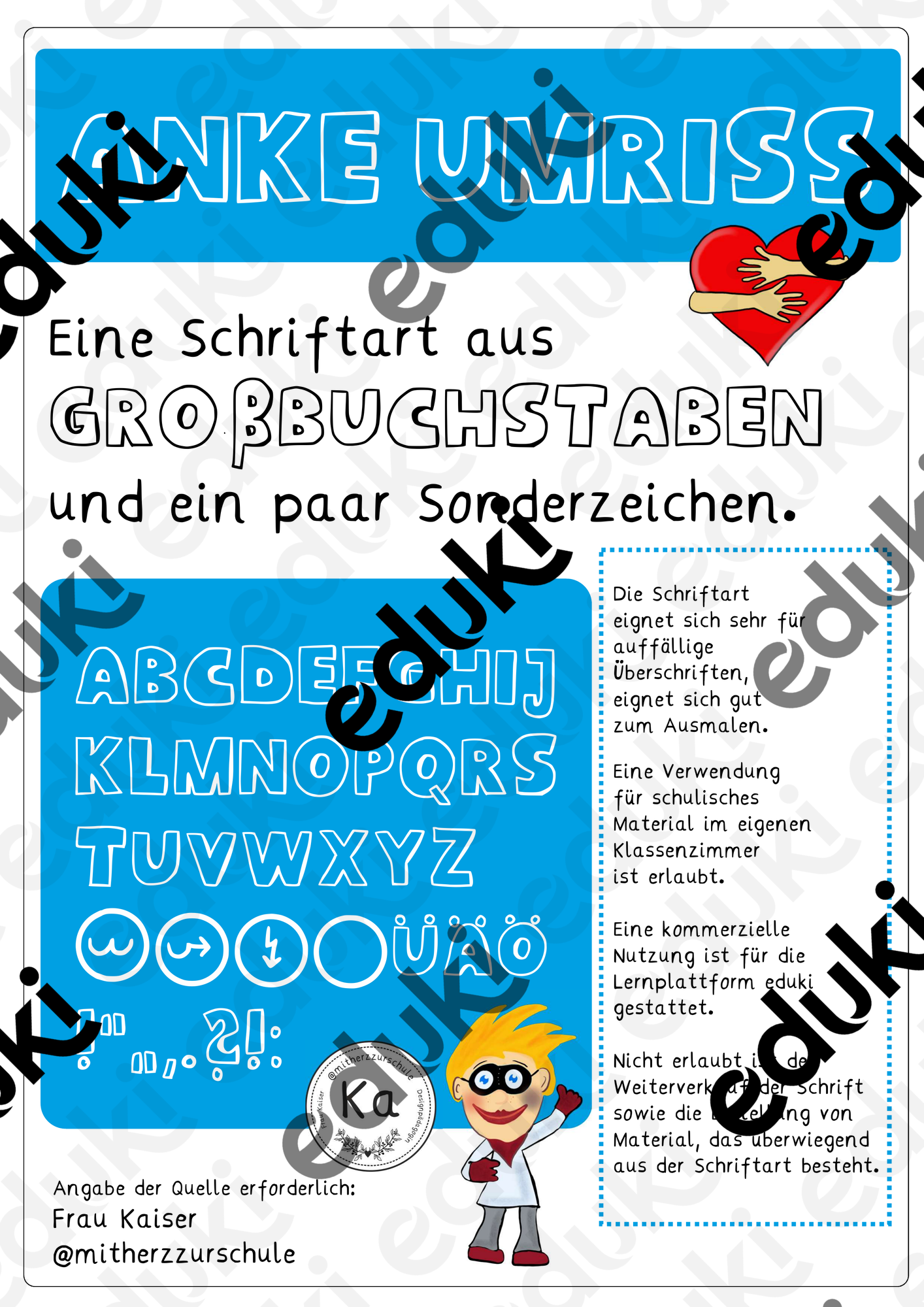
selbst erstellte Schriftarten - Schriftart Anke Umriss 2 Großbuchstaben - Frau Kaiser - Deckblatt
Eine schöne Schriftart aus Großbuchstaben, gut geeignet für Überschriften und zum Ausmalen.
Schriftart Anke Umriss 2 Großbuchstaben